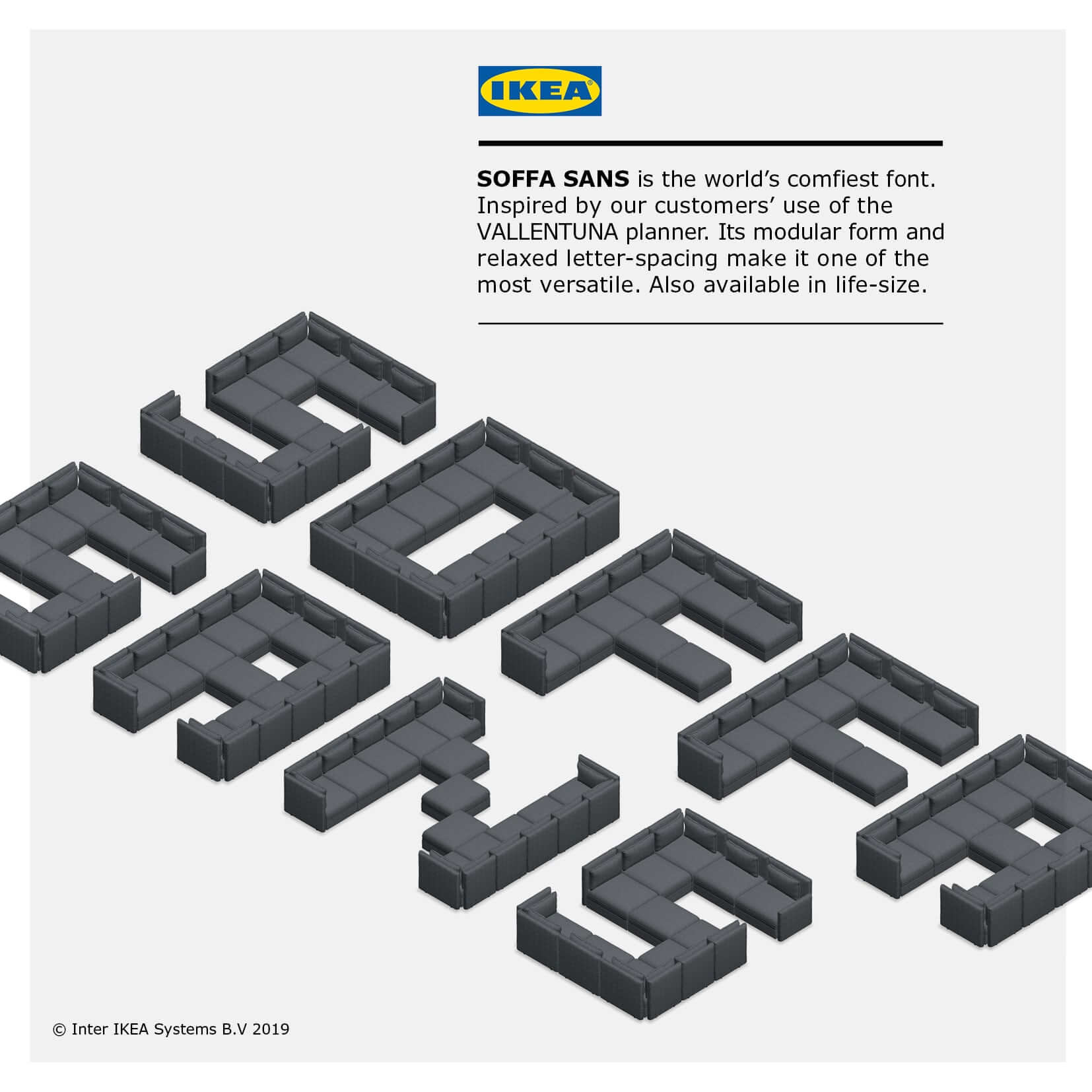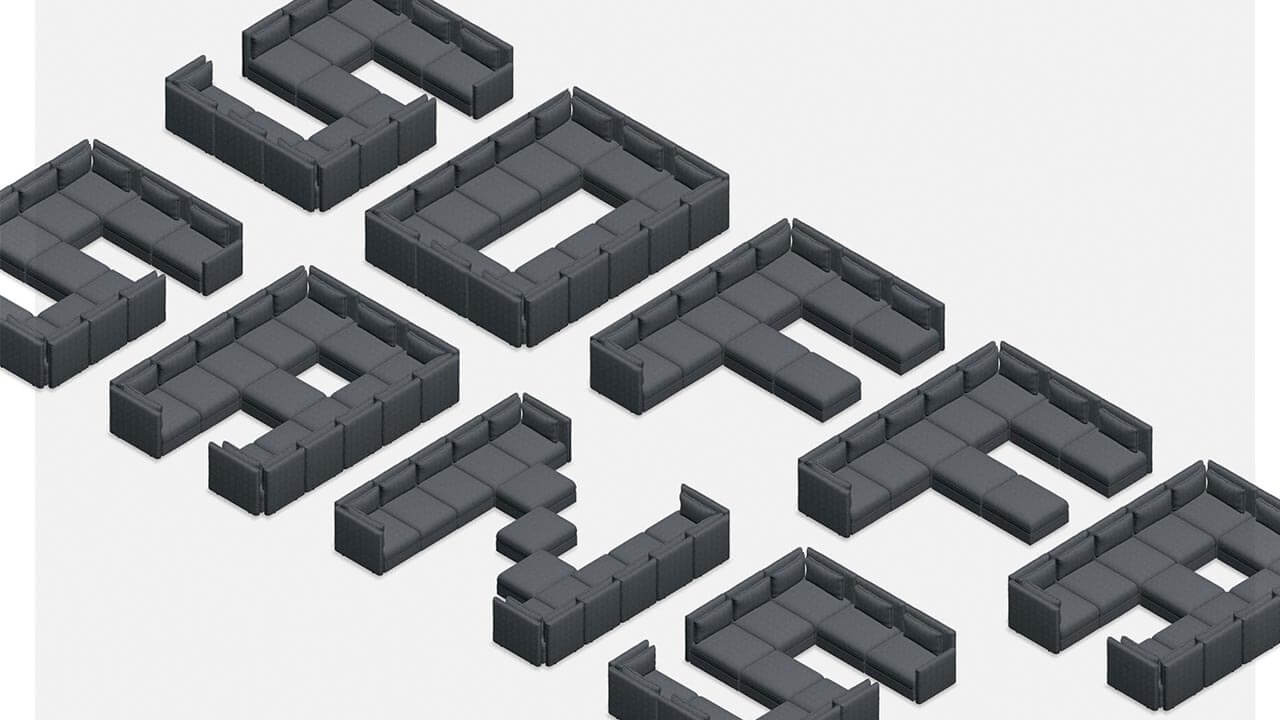
¿Es posible dar forma a todas las letras y los números del abecedario solo con muebles? Aparentemente sí, y así lo ha demostrado Ikea con el lanzamiento de Soffa Sans, una tipografía diseñada exclusivamente a partir de los productos de la marca.
Ideada por Proximity Londres, la fuente tipográfica ha sido desarrollada mediante el software Vallentuna, una herramienta de Ikea diseñada para planificar y proyectar la disposición de los sofás de la compañía.
Inspirada en la creatividad de los consumidores al momento de encontrar soluciones para sus espacios, Soffa Sans utiliza más de 140 productos de Ikea para dar forma a signos, letras y números.
“Disfrutamos viendo cómo se divierte la gente con nuestros sofas y cómo crean innovadoras soluciones. Inspirados en su creatividad, lanzamos Soffa Sans: la tipografía más cómoda del mundo. Su forma modular y el amplio espacio que deja entre los caracteres hace que sea una de las tipografías más versátiles del mercado. Estamos deseosos de ver dónde se usa”, ha comentado Marcos Tejedor, Responsable de Ventas del sector living para Ikea Reino Unido e Irlanda.